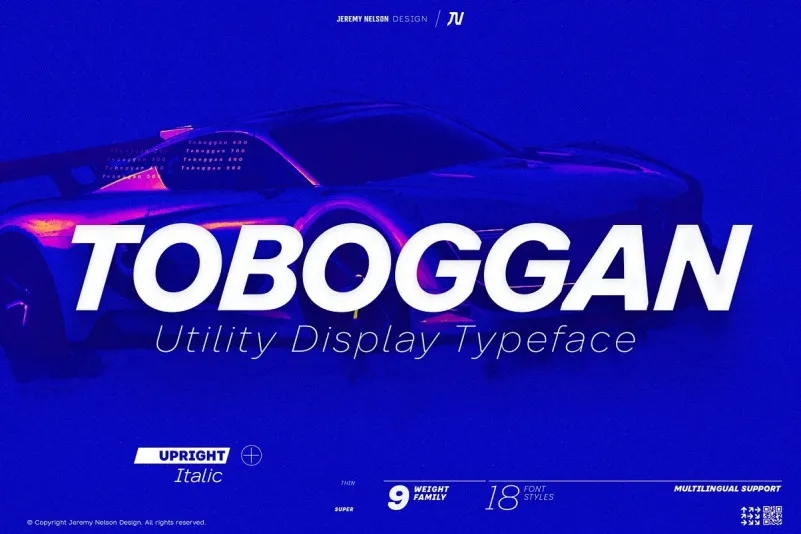
A Toboggan é uma fonte sans-serif moderna e minimalista, projetada para um design neutral com elementos decorativos sutis. Com 9 pesos diferentes – incluindo itálico verdadeiro, tanto na posição como no contrário – essa fonte se destaca por sua condensação elegante que a torna ideal para designs de gráficos modernos e criativos. Seja você um designer ou um criador digital, a Toboggan é uma escolha inteligente para seus projetos, oferecendo flexibilidade com seu total de 18 fontes em uma variedade de pesos. Combinada à sua natureza clean e simples, esta fonte pode ser a solução perfeita para qualquer projeto que necessite de um design minimalista ou moderno. Descubra por si mesmo o poder da Toboggan e inspire-se com essa opção versátil de design.